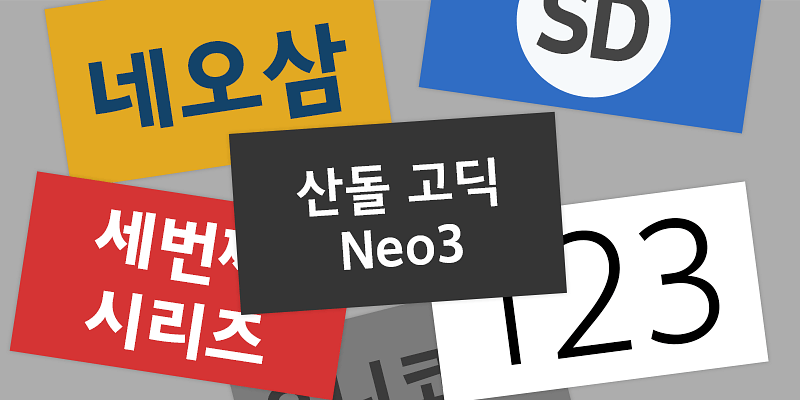
Sandoll GothicNeo3 est une police gothique de qualité supérieure, avec une superfamille de différentes graisses. Cette police de haute qualité fait partie de la gamme Sandoll Neo Series, et combine l’expertise et la technique de Sandoll, conçue pour apparaître beaucoup plus moderne et élégante que les polices Sandoll Gothic antérieures. Elle a été pensée pour assurer un confort d’utilisation, sa forme non carrée lui conférant une impression de vitalité et de liberté.